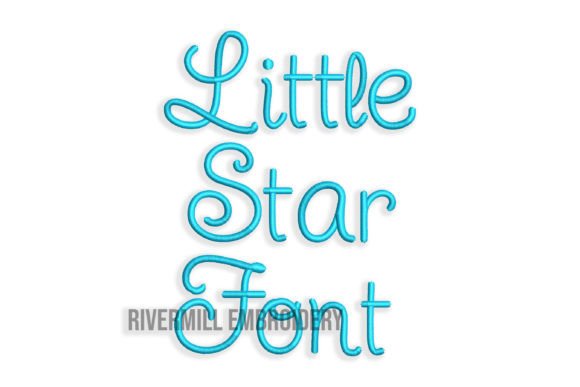
2" Little Star Embroidery Font
Trouver les bons éléments de conception peut être un défi, mais 2" Little Star Embroidery Font propose une collection exceptionnelle qui rehausse instantanément votre travail.
Conçu avec précision, 2" Little Star Embroidery Font offre des vecteurs nets, une typographie fluide et une licence commerciale pour une tranquillité d'esprit.
Que vous créiez des produits POD (impression à la demande), des invitations de mariage ou des visuels pour les réseaux sociaux, 2" Little Star Embroidery Font est un choix idéal.